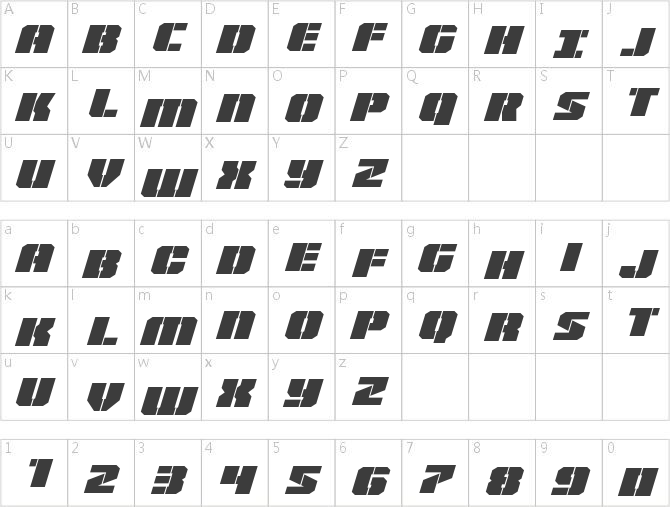
Warp Thruster Expanded Italic
Warp Thruster Expanded Italic字體字庫是一款讓人賞心悅目、百看不厭的英文字體,適合各類廣告和產(chǎn)品包裝設計應用,字體大小0.02MB,格式為ttf字體,上傳用戶是 造物設計師,作者/版權(quán)方為未知